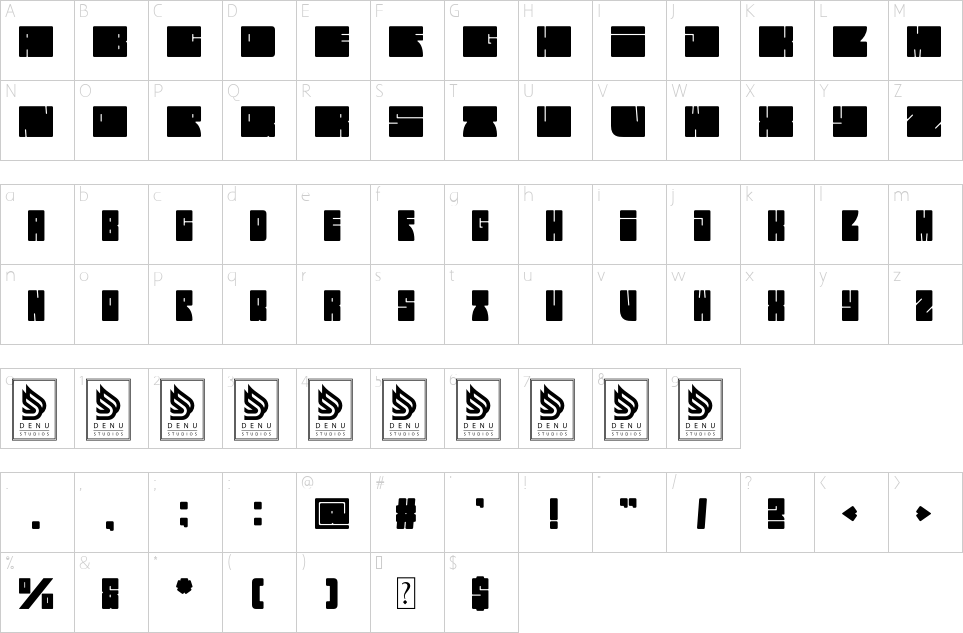
Mega Buns Font | 1001 Free Fonts – Fonte Grátis
A fonte ‘Mega Buns Font’ é um recurso gráfico gratuito e versátil para designers e criativos. Ela foi criada por Denustudios e já foi baixada por 238 usuários. Esta fonte é uma ótima opção para estilos de design que valorizam a simplicidade e o brilho, capaz de dar um toque único e divertido a qualquer projeto. Com aparência atraente e fácil de se usar, a ‘Mega Buns Font’ é perfeita para criar logotipos, efeitos visuais, designs de websites e qualquer outro tipo de projeto visual. Não perca esta oportunidade de adicionar um toque especial a seus trabalhos com esta fonte grátis.